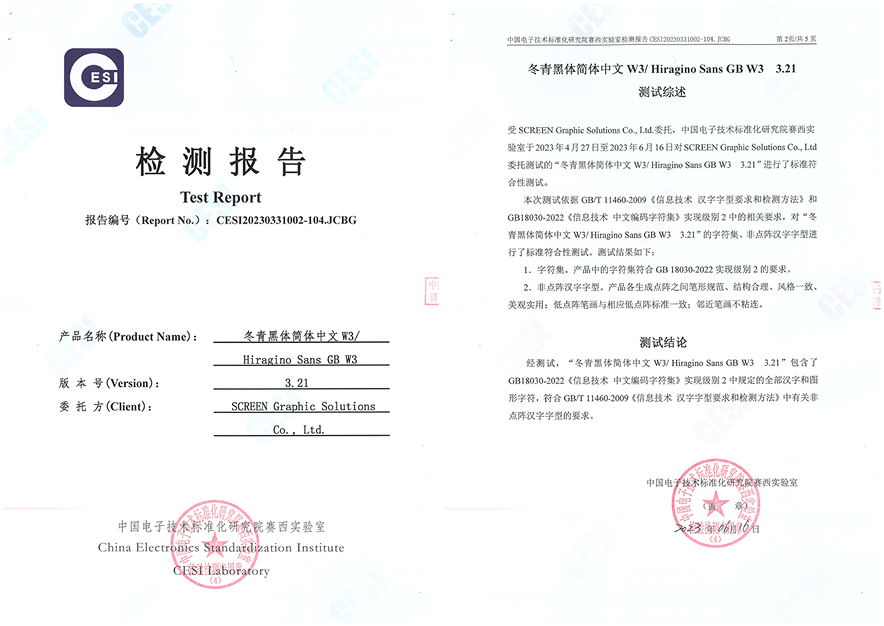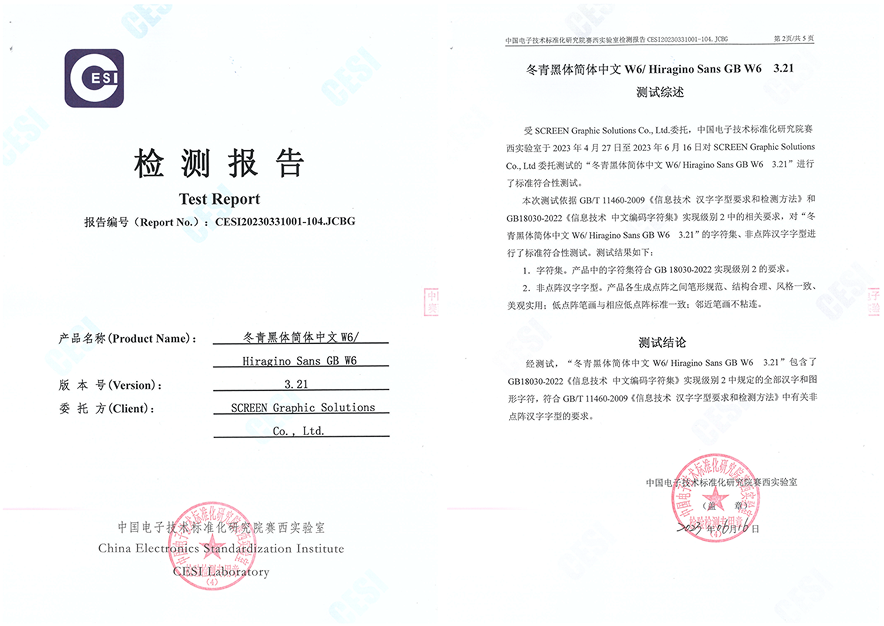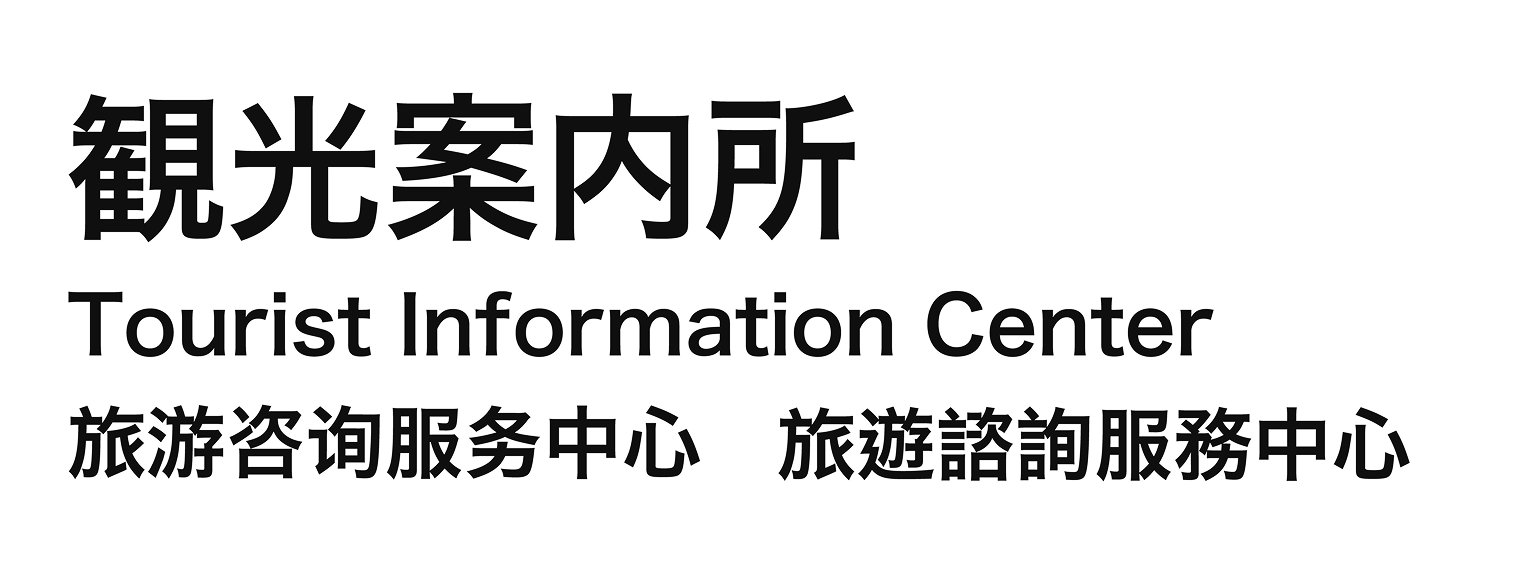
ヒラギノ角ゴ 简体中文
ひらぎのかくご かんたいちゅうぶん
Hiragino Sans Simplified Chinese
ひらぎのかくご かんたいちゅうぶん
Hiragino Sans Simplified Chinese
ヒラギノ角ゴのデザインを継承し、日中2カ国語を併記する場合でも、統一感を保ったテザインを実現させる中国語簡体字フォントです。その現代的な字形と、細部にまでこだわった品質の高さは既存の中国語フォントと一線を画しています。
7ウエイト(W0/W1/W2/W3/W4/W5/W6)のウエイトバリエーションを持ち、Webサイト、商品パッケージやカタログ、案内サインなど、利用する媒体を問わない高い汎用性で、企業のVIやCIにおけるブランディングを実現します。
さらに、中華人民共和国政府の国家標準であるGB 18030-2022(実装レベル2)の適合検査に合格したフォントとして2つのウエイト(W3/W6)をご用意しています。中国向け製品の組込みフォントとしても、美しさと読みやすさの付加価値を提供します。
■中国国家標準「GB 18030-2022」について
中国の国家標準として制定された文字コード規格です。中国国家標準化管理委員会によって2023年8月1日から適用されました。強制力を持つ国家標準であるため、中国に輸出・販売する製品には、同規格に準拠したフォントを使用する必要があります。
ヒラギノ角ゴ 簡体中文(GB 18030-2022対応)W3/W6は中華人民共和国の国家標準規格「GB 18030-2022(実装レベル2)」の適合検査に合格。さらに、アドビ株式会社によって策定されたグリフセットの規格Adobe-GB1-6(Supplement 5を除く)をサポートする29,352文字(漢字27,989文字、非漢字1,363文字)を収容しています。
GB 18030-2022は中国の国家標準として制定された文字コード規格です。中国国家標準化管理委員会によって2023年8月1日 から適用されました。強制力を持つ国家標準であるため、中国に輸出・販売する製品には、同規格に準拠したフォントを使用する必要があります。
日本語書体のヒラギノ角ゴシック体のコンセプトである、現代的かつ明るく癖のないスタンダードなデザインを継承しています。複数の言語を並べて表記する案内サイン、言語を切り替えるハードウェアやアプリ、Webサイトまで幅広い多言語環境で日本語と並べても違和感がなく、読みやすさと美しさを提供します。